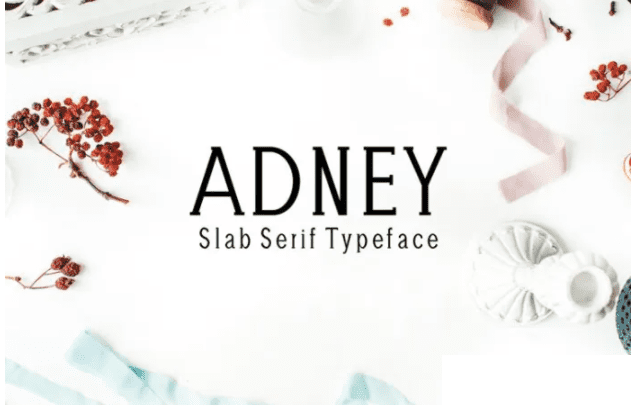
Название: Adney Font (2021)
Adney Slab Serif Typeface - набор содержит 3 веса и хорошо подходит для создания креативных отображений. Это прекрасный и уникальный шрифт Slab Serif в нашем магазине, который позволит вам сделать каждое слово совершенно стильным! Он лучше всего подходит для современных / чистых дизайнов, логотипов, заголовков, баннеров, шаблонов и т.д. Он великолепно смотрится в прописных буквах с широким интервалом, если вы хотите попробовать стильный вид, или сам по себе в прописных и строчных буквах для чего-то совершенно необычного.